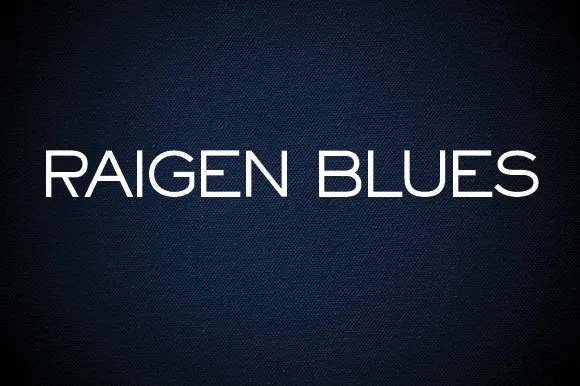
Raigen Blues Font
A Raigen Blues Font é uma fonte sans serif que transmite calma e amabilidade, perfeita para projetos visuais criativos. Desenvolvida com cuidado por Audi Prasetya, essa tipografia foi pensada especificamente para uso em trabalhos de marca e logomarcas. Seu design elegante permite uma harmoniosa combinação com um extenso conjunto de projetos, tornando-a um elemento poderoso que adiciona destaque a qualquer ideia criativa. Esta fonte é uma excelente adição ao seu arsenal gráfico, oferecendo um toque singular e profissional para seus próximos projetos visuais.